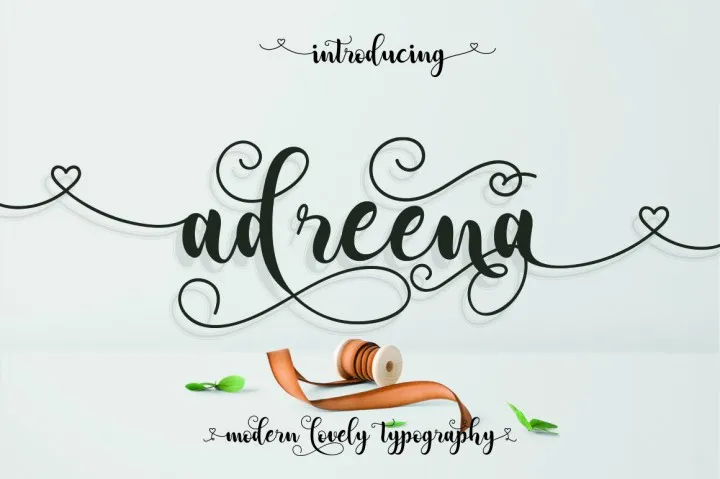
Adreena Script Font – Download Grátis
Amigos criativos! Estamos entusiasmados com a introdução do Adreena Script Font. Para designers que procuram uma novidade na área das fontes manuscritas ou góticas, este é um ótimo ponto de partida. Criado e compartilhado pela aqr.typeface, o Adreena Script oferece uma escrita com personalidade, perfeita para aplicação em várias áreas como marca, convites, camisetas, cartas de envio e outros projetos que desejam dar um toque especial. Com seu design feito cheio de amor, o Adreena Script é um recurso fantástico para qualquer projeto gráfico. Que tal experimentar a magia do Adreena Script?